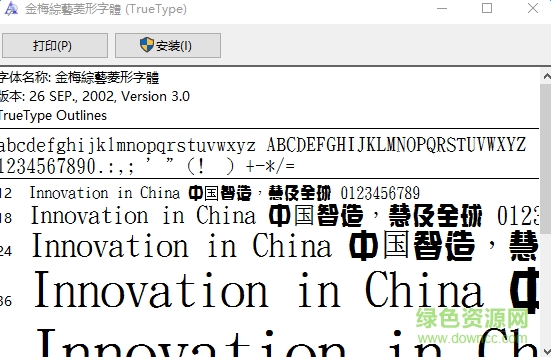
金梅綜藝菱心
金梅綜藝菱心字體是一款很有特色的電腦字體,也是實(shí)用性很強(qiáng)的一款字體,大家可以將這款字體用于很多方面,比如說書本印刷、廣告設(shè)計(jì)等都是很合適的,歡迎有需要的朋友來綠色資源網(wǎng)下載。
金梅綜藝菱心字體
金梅綜藝菱心字體是真的很不錯(cuò)的一款電腦字體,該字體寫出來的字是很好看的,也很有個(gè)性,相信大家也肯定會(huì)喜歡的,喜歡就快來綠色資源網(wǎng)下載吧。